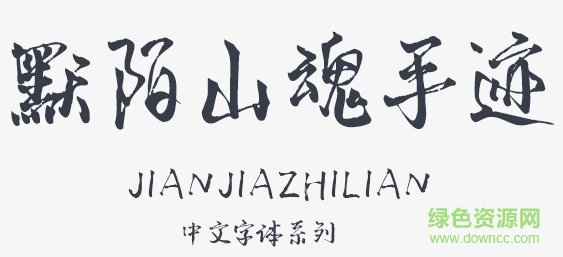
默陌山魂手跡字體是默陌字體新推出的一款手寫字體,字跡類似美工毛筆,筆觸細膩而造型干練,是一款十分清秀大方的毛筆書法字體,喜歡的朋友就來綠色資源網(wǎng)試試吧!
默陌山魂手跡字形飄逸,有著古風潑墨風格的典雅之美,同時文字造型兼具楷書和行書的大氣磅礴,給你非常舒適的視覺體驗,給你的藝術作品帶來更多獨特體驗!
默陌山魂手跡筆畫連貫而灑脫,獨有的大氣帶著古風字體的質樸和高潔的韻味,在平面設計、海報設計、包裝設計上均可以使用!